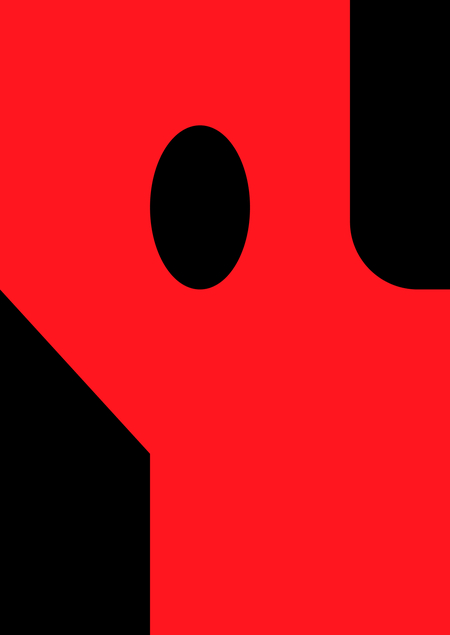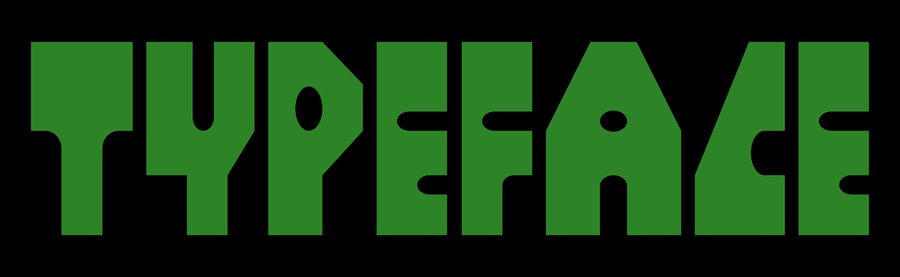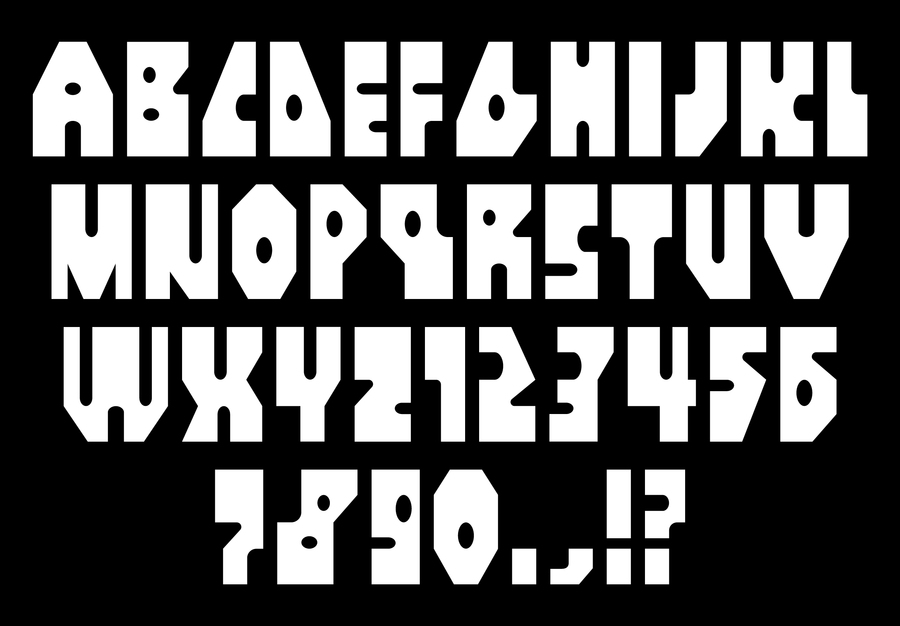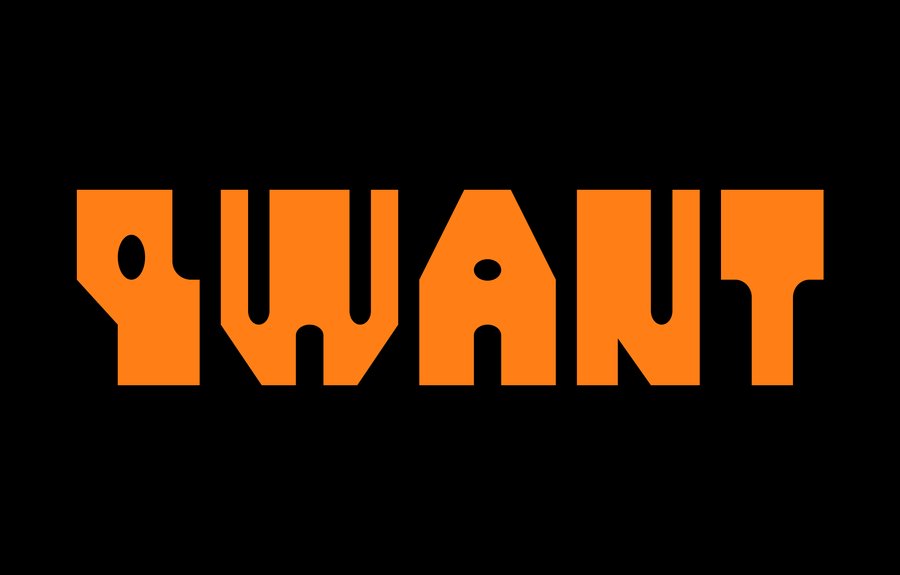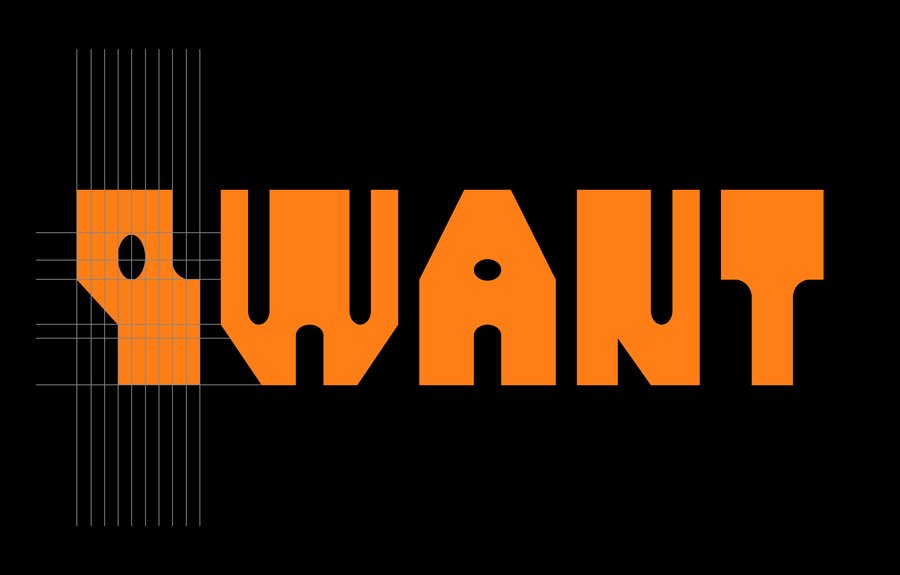
Qwant font on Mediiia
Qwant — брусковый акцидентный шрифт, одновременновдохновлённый монументальным брутализмом и ретрофутуризмом. Состоит из прямых линий, но скруглённых углов, что в сочетании отсылает к космической эстетике. Qwant полужирный, без засечек, среднего контраста.